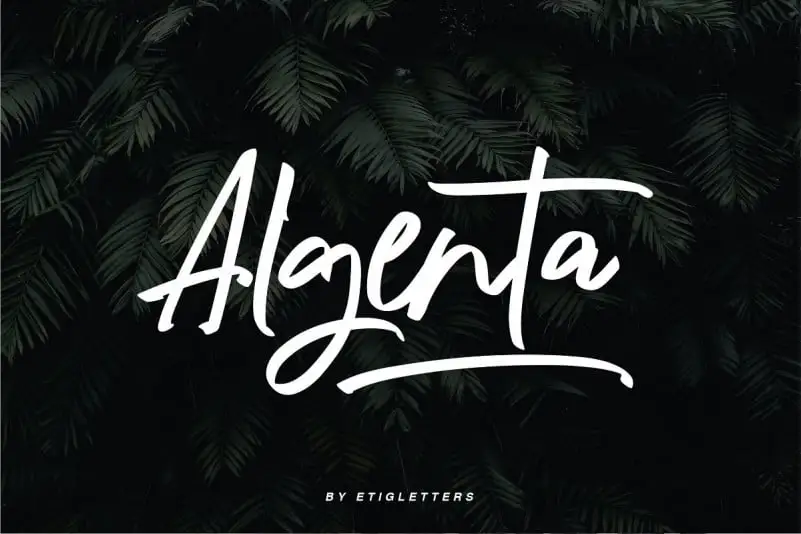
Algenta Script Font – Download Grátis
A Algenta Script é uma fonte casual que combina elementos de tipo e letra escrita a mão, trazendo um toque mais autêntico ao seu design. Essa fonte foi criada pelo designer etigletters e disponível com ligações, deslizamentos de letras e setes alternativos estilísticos. Este estilo casual traz uma personalidade única para seus projetos gráficos e torna-a perfeita para uma variedade de usos. A Algenta é ideal para criações de marca como materiais de branding, flyers promocionais, templates para redes sociais, cartões de visita, logotipos, camisetas, posters, e muito mais. Seu design elegante e atemporal certamente vai deixar sua marca em qualquer projeto em que for usada.